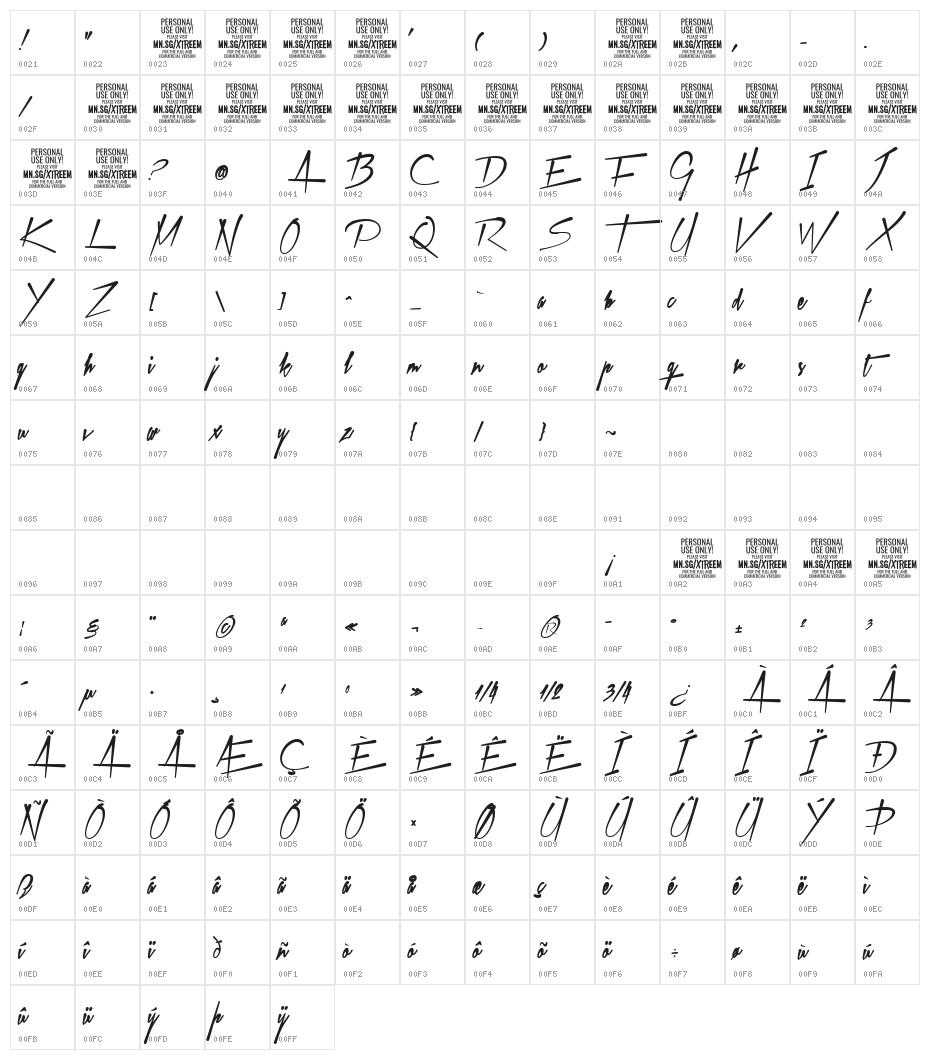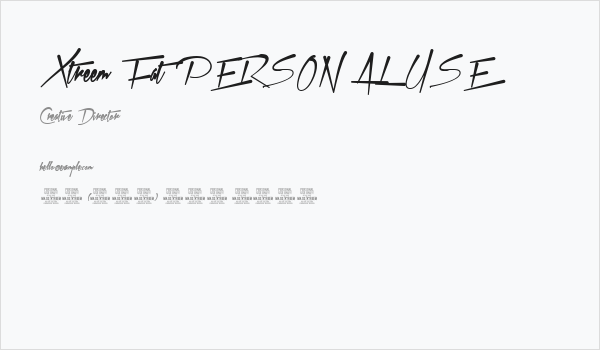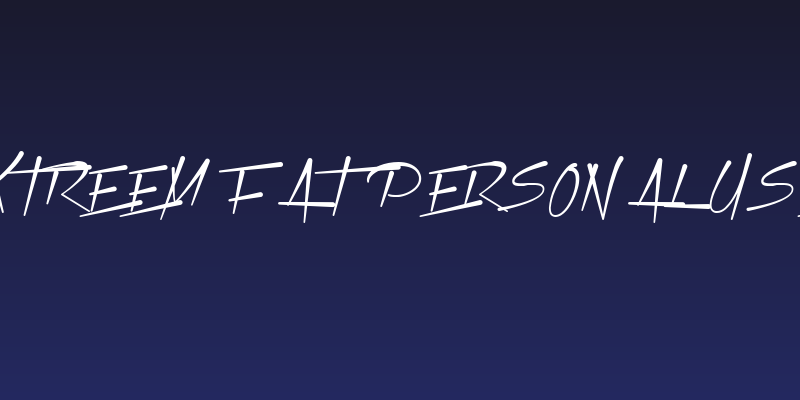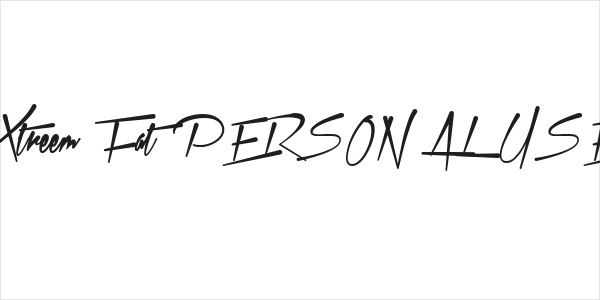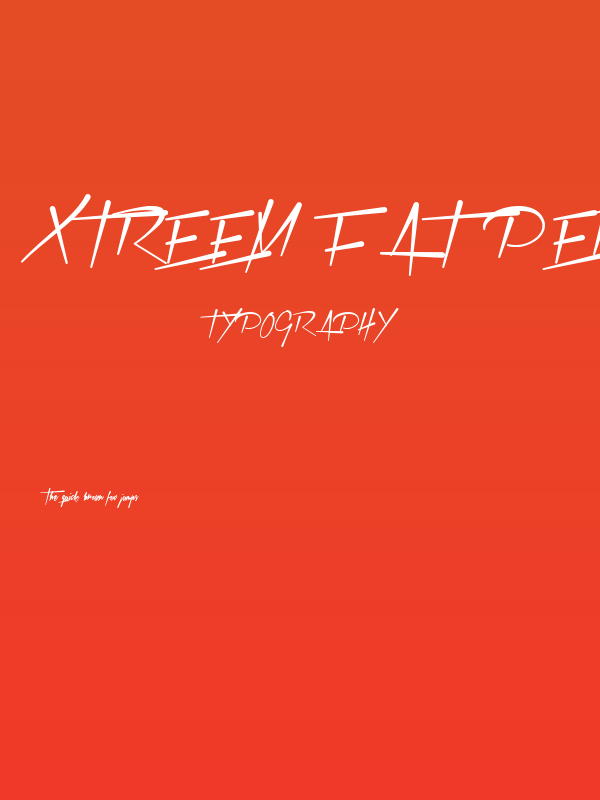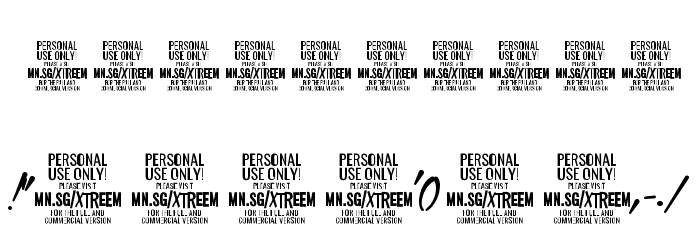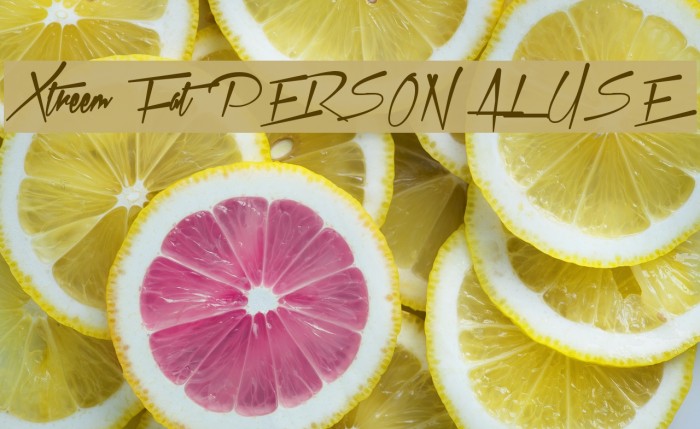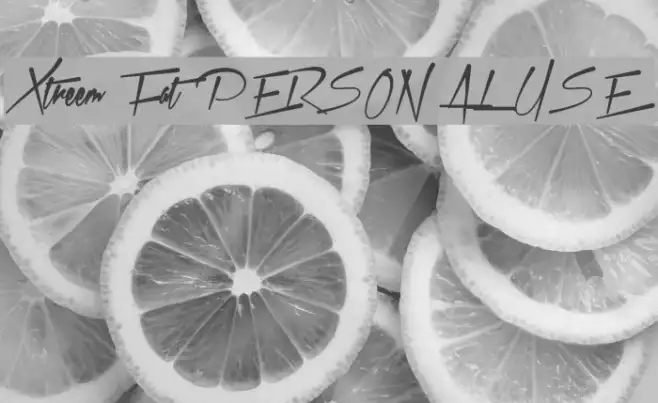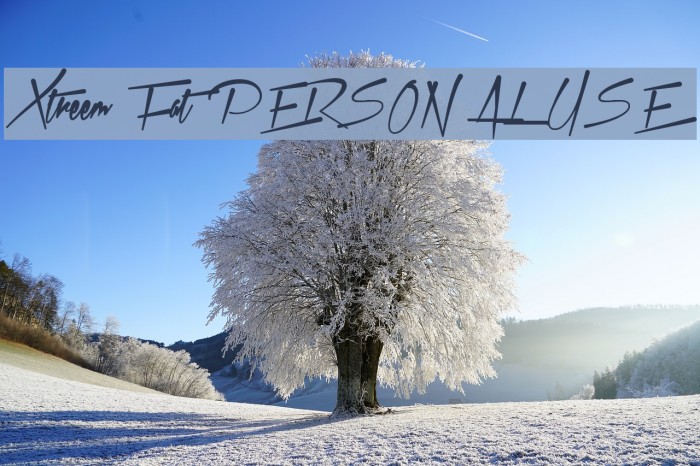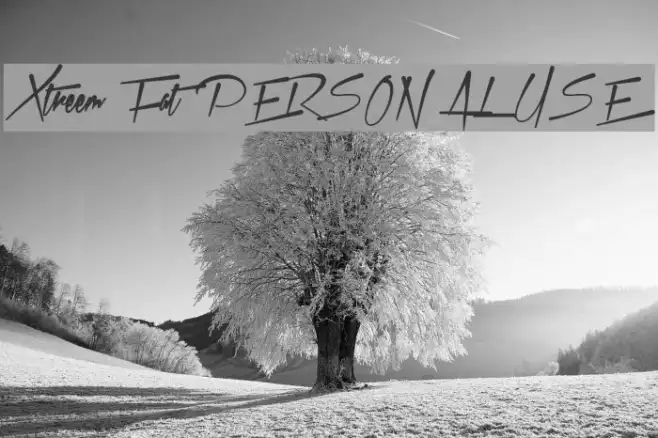
Xtreem Fat PERSONAL USE Font
| Caso de uso | Logos, Headlines, Posters |
| Proyectos propuestos | Ideal for creative projects such as posters, logos, and branding materials that require a personal and energetic touch. |